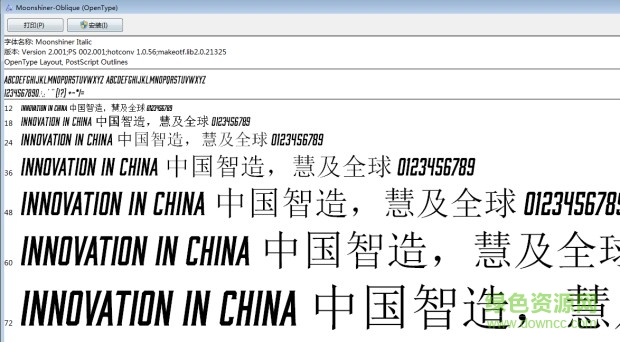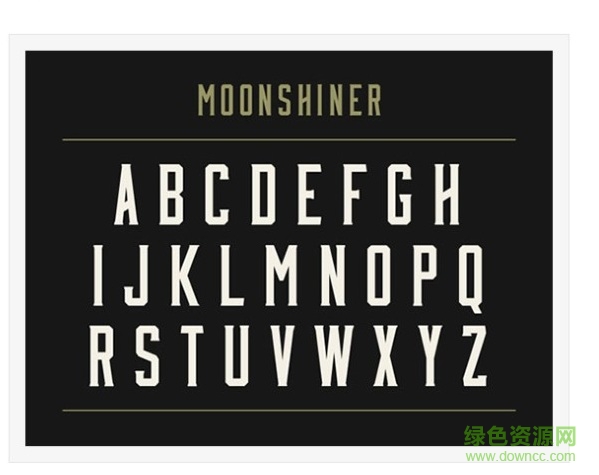
Moonshiner字體是一款超好用的英文字體,由設(shè)計師 Mattox Shuler 制作而成,極具影響力的一款標(biāo)題字體,適合圖形設(shè)計的項目。有喜歡這款字體的朋友就趕快來綠色資源網(wǎng)下載使用吧!
Moonshiner字體是一款英文字體,這款字體具有非常強的個性風(fēng)格,適合各類設(shè)計領(lǐng)域使用,有需要的朋友就趕快來綠色資源網(wǎng)下載吧!